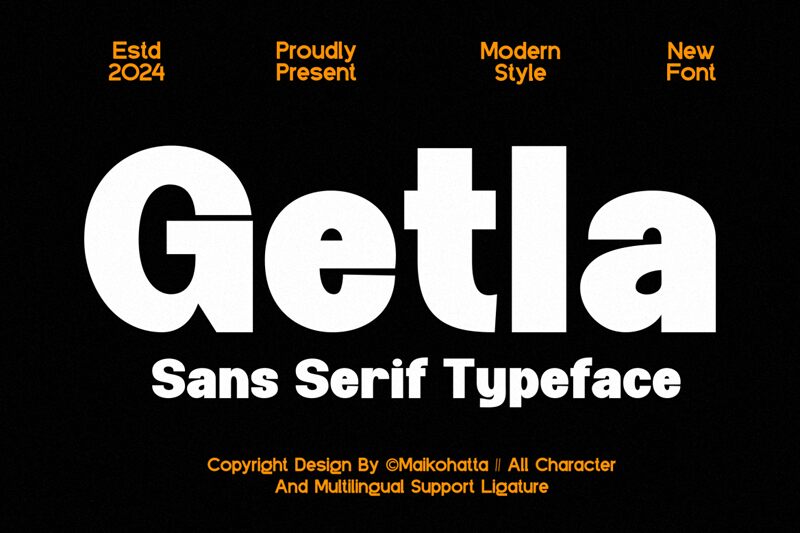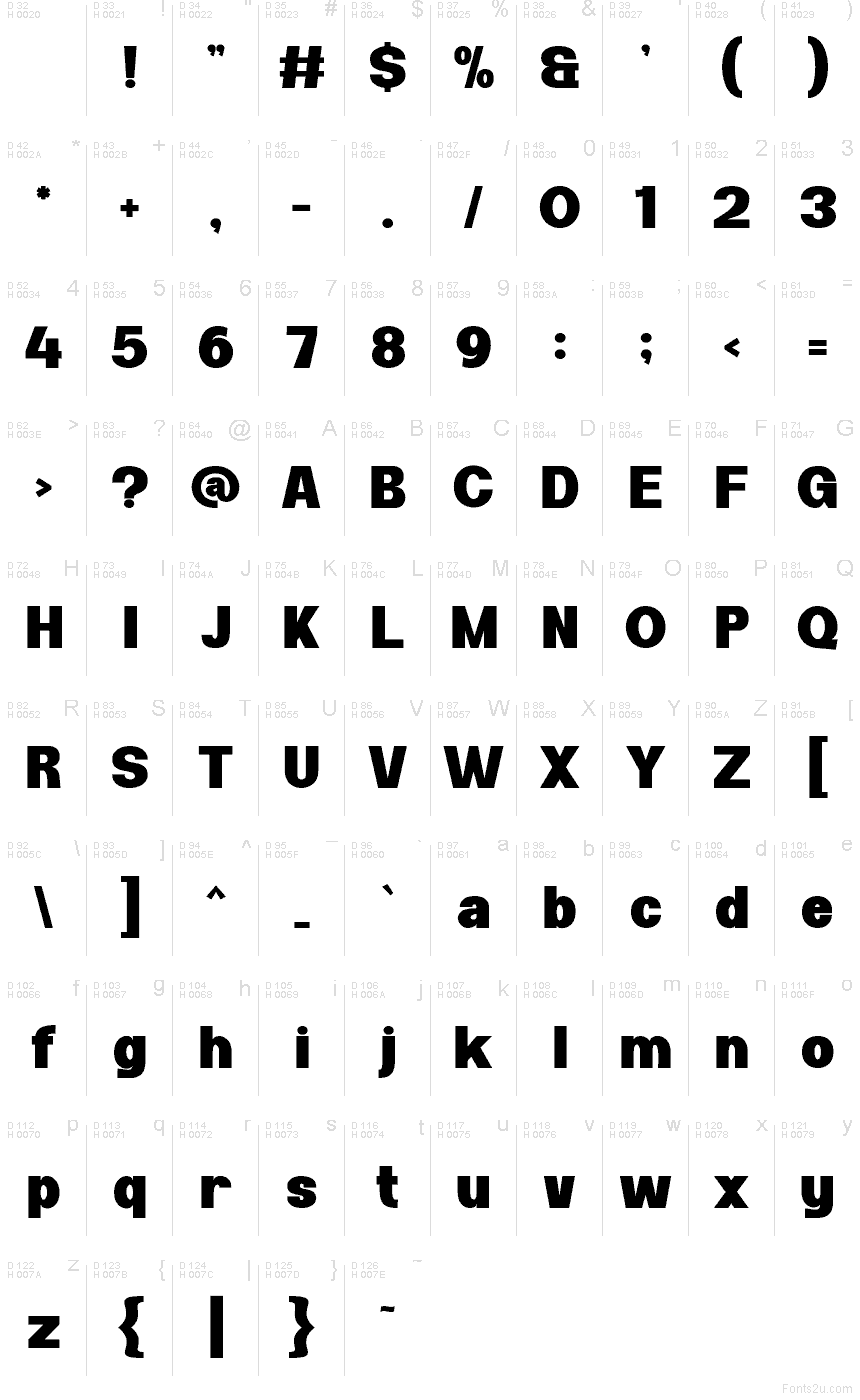
Getla od Maikohatta je bezplatné, ultra tučné geometrické bezpatkové písmo s hustou, předimenzovanou siluetou. Jeho široké křivky a masivní svislé tahy se těsně sbíhají a malé vnitřní prostory jsou ostře vyřezané do hmoty. Písmo působí stlačeným a rázným dojmem.
Značky zaměřené na streetwear, noční život nebo mládežnickou kulturu jej mohou využít na loga, plakáty a merchandising. Téměř celistvé tvary písmen proměňují názvy v kompaktní grafické tvary, díky čemuž se hodí také pro hudební akce a módní obaly. Jeho nejsilnější stránkou je výrazné nadpisové logo, kde těsné spoje a oříznutě působící tvary tvoří součást značky namísto obyčejného neutrálního textu.